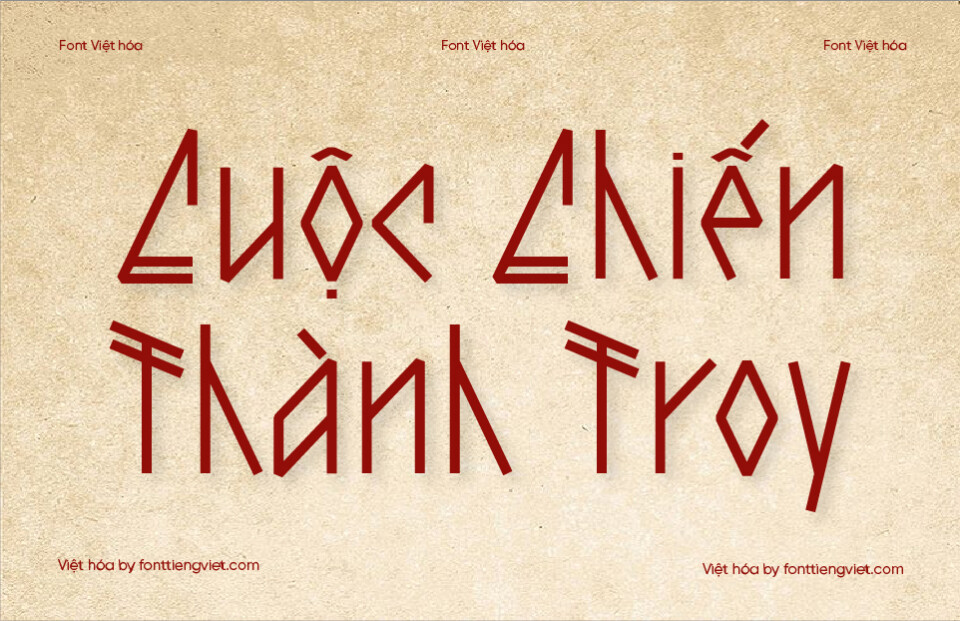
Font Việt hóa 1FTV VIP Sleipnir
Trong thế giới đồ họa hiện đại, việc lựa chọn một Font Việt hóa 1FTV VIP Sleipnir chất lượng là yếu tố then chốt giúp nâng tầm giá trị sản phẩm. Đây là bộ Font Miễn Phí được tinh chỉnh kỹ lưỡng, hỗ trợ đầy đủ bảng mã tiếng Việt với độ hiển thị sắc nét tuyệt đối. Với phong cách mạnh mẽ nhưng không kém phần uyển chuyển, bộ phông chữ này nhanh chóng trở thành lựa chọn ưu tiên cho các dự án sáng tạo cần sự độc đáo và ấn tượng ngay từ cái nhìn đầu tiên.
Đặc điểm nổi bật của Font Việt hóa 1FTV VIP Sleipnir
Thiết kế tinh xảo và đa dụng
Bộ Font Việt hóa 1FTV VIP Sleipnir sở hữu đường nét dứt khoát, mang hơi hướng hiện đại pha chút cổ điển. Cấu trúc chữ cái được tối ưu hóa để đảm bảo tính đọc hiểu cao trên cả nền tảng kỹ thuật số lẫn in ấn thực tế. Điều này giúp các nhà thiết kế dễ dàng ứng dụng vào nhiều thể loại khác nhau như làm bìa sách, thiết kế logo, hay tạo các ấn phẩm truyền thông cho trường học và doanh nghiệp.
Tương thích hoàn hảo với tiếng Việt
Khác với các bộ phông chữ nước ngoài thông thường, phiên bản VIP Sleipnir này đã được Việt hóa chỉn chu. Các dấu câu và ký tự đặc biệt được đặt ở vị trí hợp lý, tránh tình trạng bị lỗi hiển thị hoặc lệch dòng khi gõ văn bản dài. Nhờ vậy, người dùng có thể tiết kiệm tối đa thời gian chỉnh sửa thủ công, tập trung hoàn toàn vào việc sáng tạo nội dung một cách hiệu quả nhất.
Cách ứng dụng Font Việt hóa 1FTV VIP Sleipnir hiệu quả
Để tận dụng tối đa vẻ đẹp của phông chữ này, bạn nên sử dụng cho các tiêu đề lớn hoặc câu trích dẫn quan trọng. Việc kết hợp Font Việt hóa 1FTV VIP Sleipnir với các phông chữ không chân (sans-serif) đơn giản sẽ tạo ra sự tương phản thú vị, giúp bố cục thiết kế trở nên cân đối và chuyên nghiệp hơn. Đừng ngần ngại tải về bộ Font Miễn Phí, Font Việt Hóa, Font Việt hóa 1FTV VIP Sleipnir để trải nghiệm ngay hôm nay và tạo nên những tác phẩm nghệ thuật thực thụ cho riêng mình.